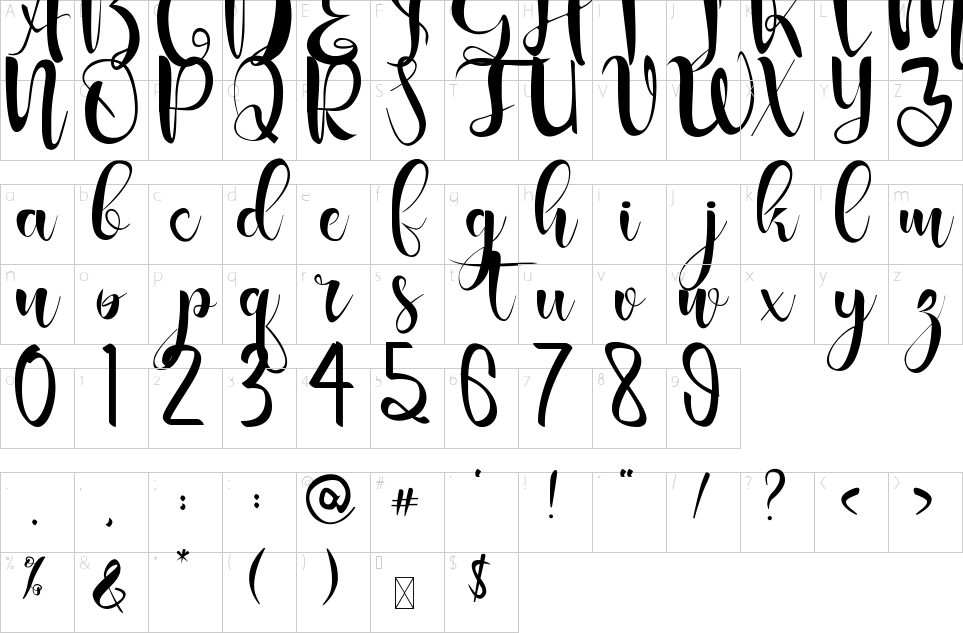
A fonte ‘Perfect Stenlies’ é uma opção de fonte grátis que oferece uma experiência visual agradável, com um design limpo e atraente. Esta fonte foi criada pelo designer desconhecido da InermediaSTUDIO e já foi baixada 341 vezes. Se você está procurando por uma fonte de alto padrão para projetos de design, ‘Perfect Stenlies’ é uma excelente escolha, adequada tanto para o Windows quanto para o Mac. Suas linhas sóbrias e equilibradas proporcionam um equilíbrio perfeito entre clareza e elegância, tornando-a uma fonte versátil que se adapta bem a diferentes estilos de design. Seja para criar logotipos, design de página web ou qualquer outro projeto de design, ‘Perfect Stenlies’ pode ser a fonte perfeita para sua necessidade.